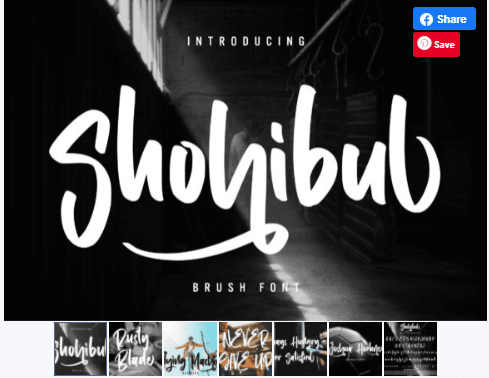
Shohibul Font
Shohibul - это живой и необычный рукописный шрифт. Это придаст вашему дизайну свежий и современный вид. Добавьте этот уникальный дисплейный шрифт к каждой своей творческой идее и обратите внимание на то, как он выделяет их!